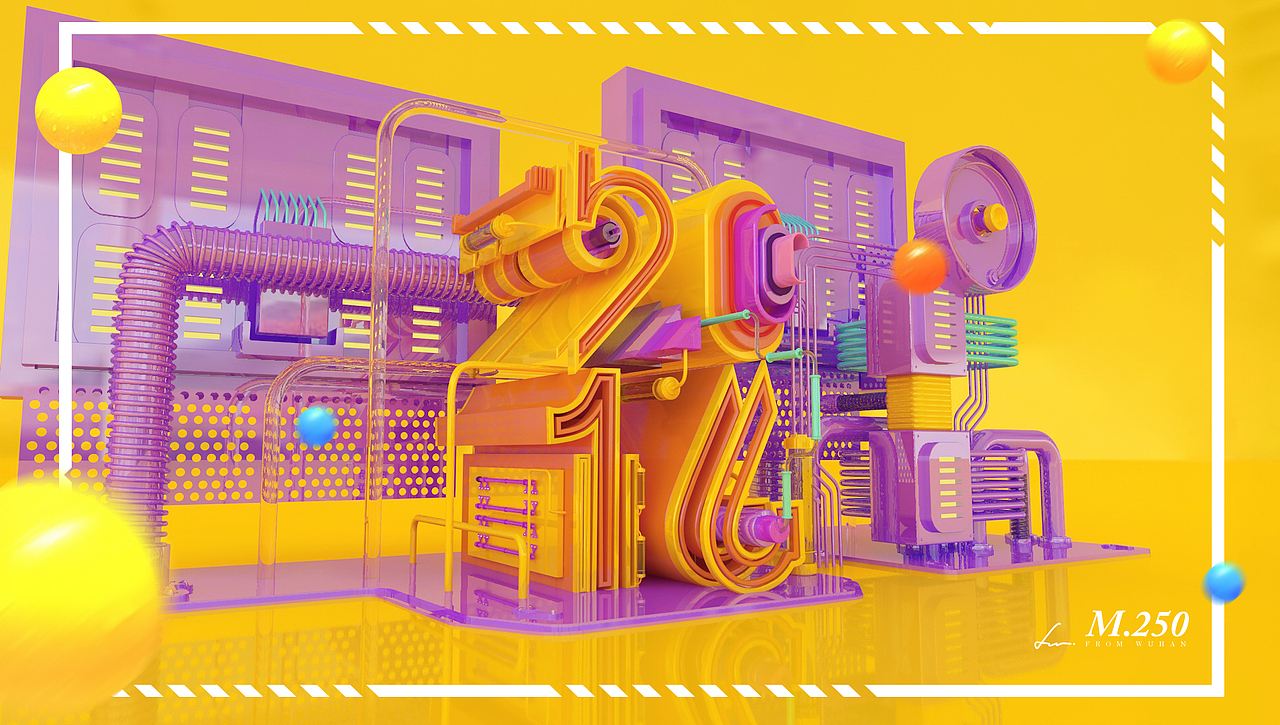
C4D字体练习【2016色起来GOGOGO】
C4D终于不再是暗黑系了,难得走了一回小清新路线,都不敢相信这是我做的哈哈哈哈哈~
2016字体造型有参考BEHANCE大神的图,其他都是自己慢慢磨出来的
怎么办~~这颜色玩的欲罢不能呀!!C4D有毒!!
最终选了老白最爱的粉嫩系当头牌
4款老白最爱的清爽明亮色系
老白最爱的基佬紫
差点流产的黑金也出来献献丑吧